「活字は印刷の元や(関西弁)!」モトヤの社名ルーツです。
文字やフォントって、日頃あまり意識しないで利用していますが、無くてはならない存在です。文字が存在しなかったら、看板や標識は役に立たなくなります。表現豊かな様々なフォントが存在しなければ、デザインやコンテンツの楽しさが半減します。そんな素敵な文字達を作っているフォントメーカーを紹介する連載ブログ。今回取り上げるのは「モトヤ」です。
フォントメーカー「モトヤ」の社名の由来
株式会社モトヤは大正11年(1922年)に兵庫県姫路市において活字の製造販売・印刷材料の販売で創業し、今年で100周年を迎えるフォントメーカーです。モトヤは、1949年に活字を鋳造するための母型を製作するベントン彫刻機を導入します。活字の母型を作るためには、文字パターンの元になる原字が必要になります。その歴史的背景から、モトヤにおいて書体デザインの仕事がスタートします。ちなみに、モトヤの社名の由来は、「活字は印刷の元や」という関西弁からきているそうです。社名のルーツ話が素敵ですね。
70年を超えるモトヤ書体の歴史を辿ってみると、組版手法や利用目的など、その時代のニーズに応じて、フォントの製品形態が変化してきました。鉛活字・タイプ活字・デジタルフォント(ビットマップフォントやアウトラインフォント)など、時代にあった製品を作り続けています。永年にわたる書体開発の歴史の中で、モトヤが変わらないもの、それは、「可読性の良さ」と「文字の美しさ」の追求とのことです。
鋳造活字からデジタルフォントにいたるまでの歴史
大阪の南船場にあるモトヤ本社へ仕事で定期的にお伺いした中で、本社建物の一角にある「活字資料館」も数回見学しました。えっ、活字資料館って何? モトヤは鋳造活字メーカーでしたので、この100年間の日本語活字の変遷が展示されているのです。
モトヤ活字資料館を初めて見学したのは2011年。この資料館、歴史好きにとっては感動ものでした。活版印刷の機材からタイプライター・DTPシステム・デジタルフォントに至るまでの資料や機材が、時系列に展示してあるのです。あわせて、フォントの設計工程・活字の製造工程・植字台で組版する工程が理解できるよう、部品や治具の展示、それらを説明するパネルが掲示されています。明治から現在に至るまでの日本語活字の歴史を、実物を見ながら、わかりやすく学ぶことができるのです。
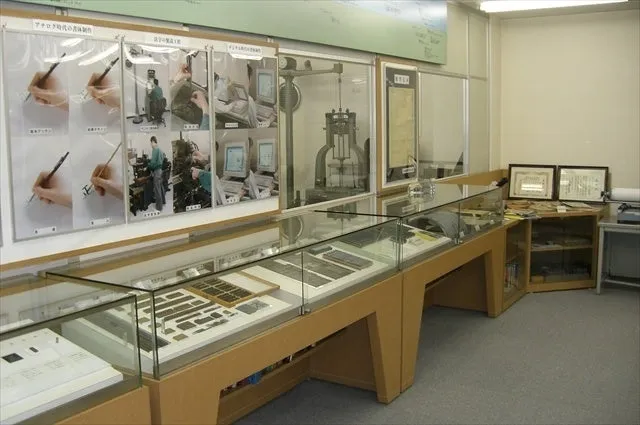
活字を鋳造し、活版印刷の版ができるまで
それでは、活字資料館の写真を何枚か掲載しながら、鋳造活字が製造される過程を簡単にご紹介します。
1)ベントン彫刻機
清書した文字の原図を基にしたパターン(亜鉛版)をなぞりながら、活字の母型(金型のようなもの)を作るのが、ベントン彫刻機です。この装置を操作してきれいな母型を作るのには熟練された技が必要だそうです。活版印刷で使われる鋳造活字は、日本語の文字の数だけ母型を作る必要があります。そして、サイズ単位(5号とか6号とか)毎に、活字を用意しなくてはなりません。それらの活字を鋳造するためには、母型が必要になるのです。
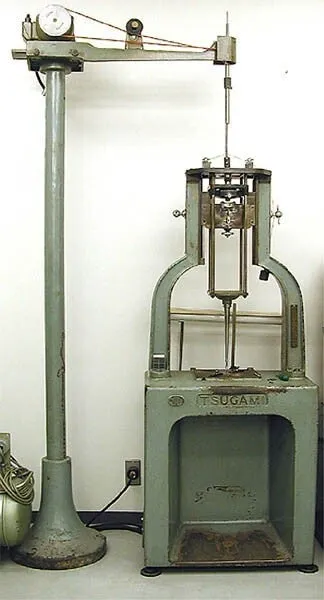
2)活字鋳造機
母型に地金を流し込んで活字を製造する機械です。地金の主な成分は鉛で、スズやアンチモンという素材も混ぜるようです。地金を熱して液状になったものを母型に流し込み、冷やすと、凸型の活字が完成します。
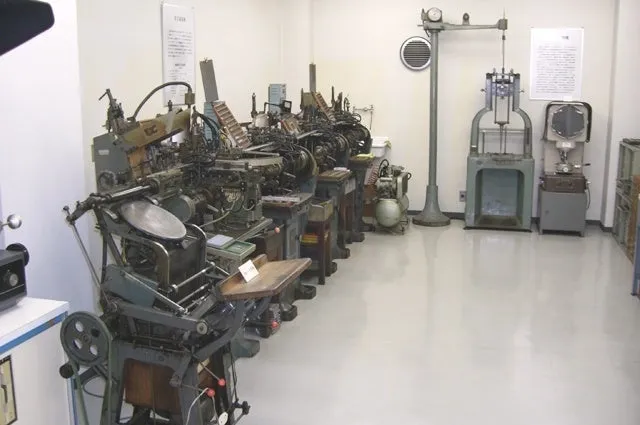
3)植字台で組版
鋳造活字が並べられた活字棚から活字を一つ一つ拾い(文選といいます)、そのあと、植字台で文字間や行送りを調整する小さいパーツ(インテルやクワタ)と組み合わせながら活字を組版していきます。最後に枠を糸でしっかりと縛ります。1万字以上ある膨大な日本語活字を文選して組版する作業ってすごいです。「文字を紡ぐ」という感覚ですね。
ところで、それぞれの文字、何本ずつ製造するのでしょうか? 例えば、ひらがな「の」は使用頻度が高いのでたくさん作る必要があったそうです。今なら、ビッグデータ分析で、文字の使用頻度の分布が数値化できますが、その頃は、経験値の積み上げから判断していたようです。また、小説と週刊誌とでは、よく使われる文字の傾向は違うでしょうし、業界毎に特殊文字や外字が存在するので、特注で文字を鋳造することもあったとお聞きしました。
書体毎に「原字」(文字デザイン)を作成し、そこからベントン彫刻機で母型を作り、鋳造機で金属活字をサイズ毎に製造するといった作業を、モトヤでは行っていたのです。デジタルフォントの世界から比べると気が遠くなる作業です。そんな文字の歴史を知ってしまうと、文字がますます愛おしくなります。
和文タイプライター、DTPシステムへ
欧文の活字タイプライターの文字の数は100字あれば、通常は間にあいます。ところが、日本語のタイプライターを作ろうとすると、必要な文字数って膨大です。日本語は英文の字数に比べて100倍以上ありそうです。モトヤ活字資料館には、日本語タイプライターのような機材が展示してありました。欧文タイプライターのようにタイピングしないので日本語タイプライターという表現は正しくないのかもしれません。資料館に展示してある活字組版装置には日本語の金属活字がずらっと収まっていました。それらの活字を拾い上げ、紙が巻いてあるプラテンに打鍵するとインクリボンから紙に文字が転写されて文章が完成するのです。文字を拾う方法は、手動で必要な文字を一つ一つ拾う方式と、文字盤から拾って電動式で活字を打鍵する方式がありました。
商品名にモトヤ「タイプレス」と書かれています。この「タイプレス」という組版機は、1970年代に広く普及していました。
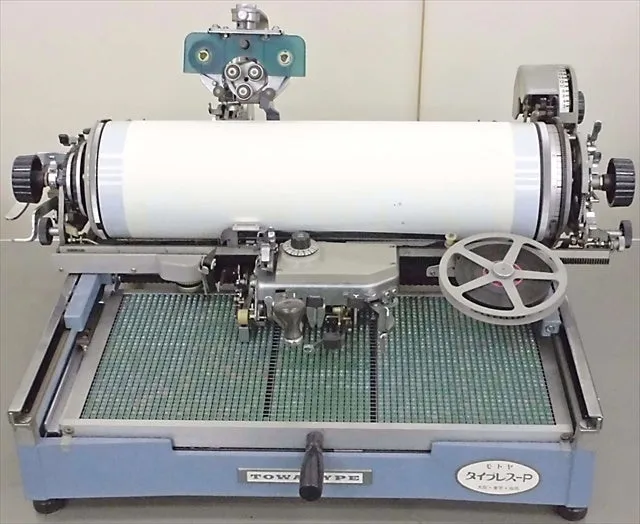
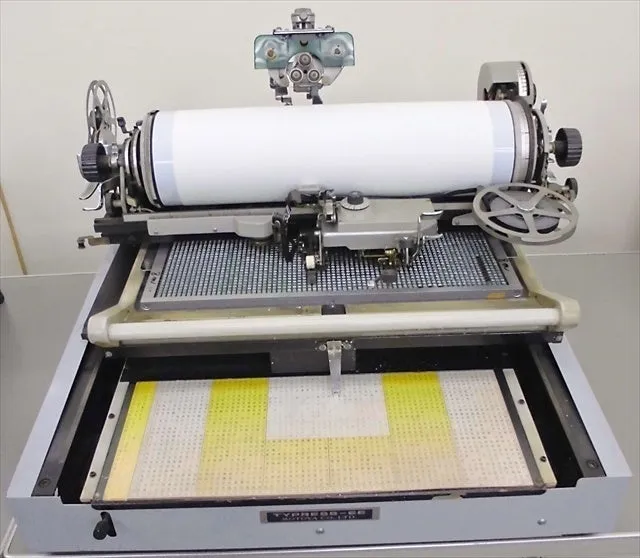
1980年代初頭に電子編集可能な組版機器が普及しはじめます。モトヤでは、1982年に「電子編集組版機WP-6000」を九州松下電気と共同開発しワープロの長所を取り入れた組版機を発売します。1985年にはレーザープリンタを搭載した「電子編集組版システムLASER7」シリーズが発売され、1988年にこの機材の分野にて販売量で業界シェア1位になりました。
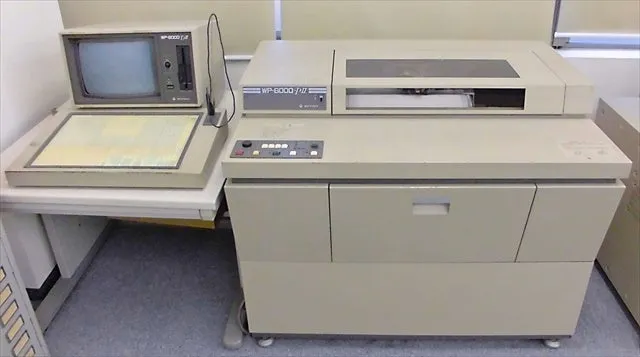
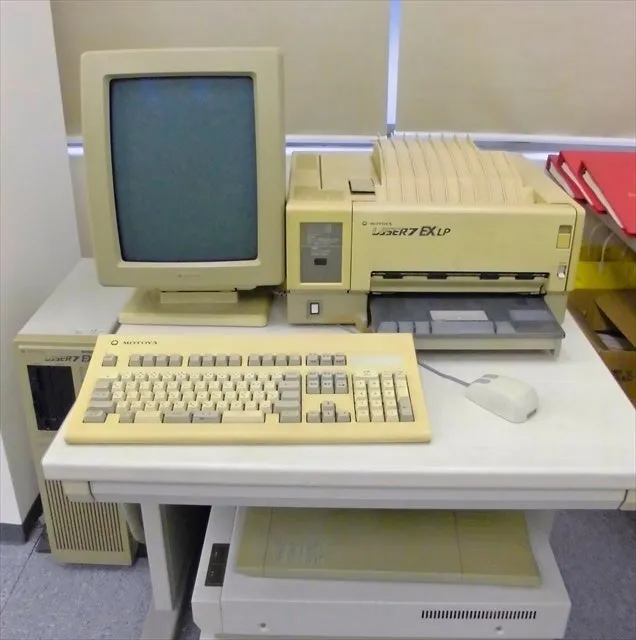
1980年後半、パーソナルワープロが家庭に普及し、ワープロの累計出荷台数は2,000万台を超えたと言われています。当時のワープロ専用機の多くに、モトヤの明朝体(ドットフォント)が採用されていました。また、モトヤ書体は写真植字(写植)のメーカーへも提供されました。
その後、インターネットの普及により、パソコンやスマホの画面越しにフォントを目にする機会が増え、時代が文字に求めるニーズはデジタルフォントへ変化しました。地図メーカーのウェブサイトではモトヤフォントが採用され、スマホメーカーのシステムフォントにも採用されました。パソコンやインターネットで求められるフォントサービスに柔軟に対応しています。
モトヤ書体の紹介
FONTPLUSで使えるモトヤ書体(69書体)の中から、主な書体をためし書きしてみました。
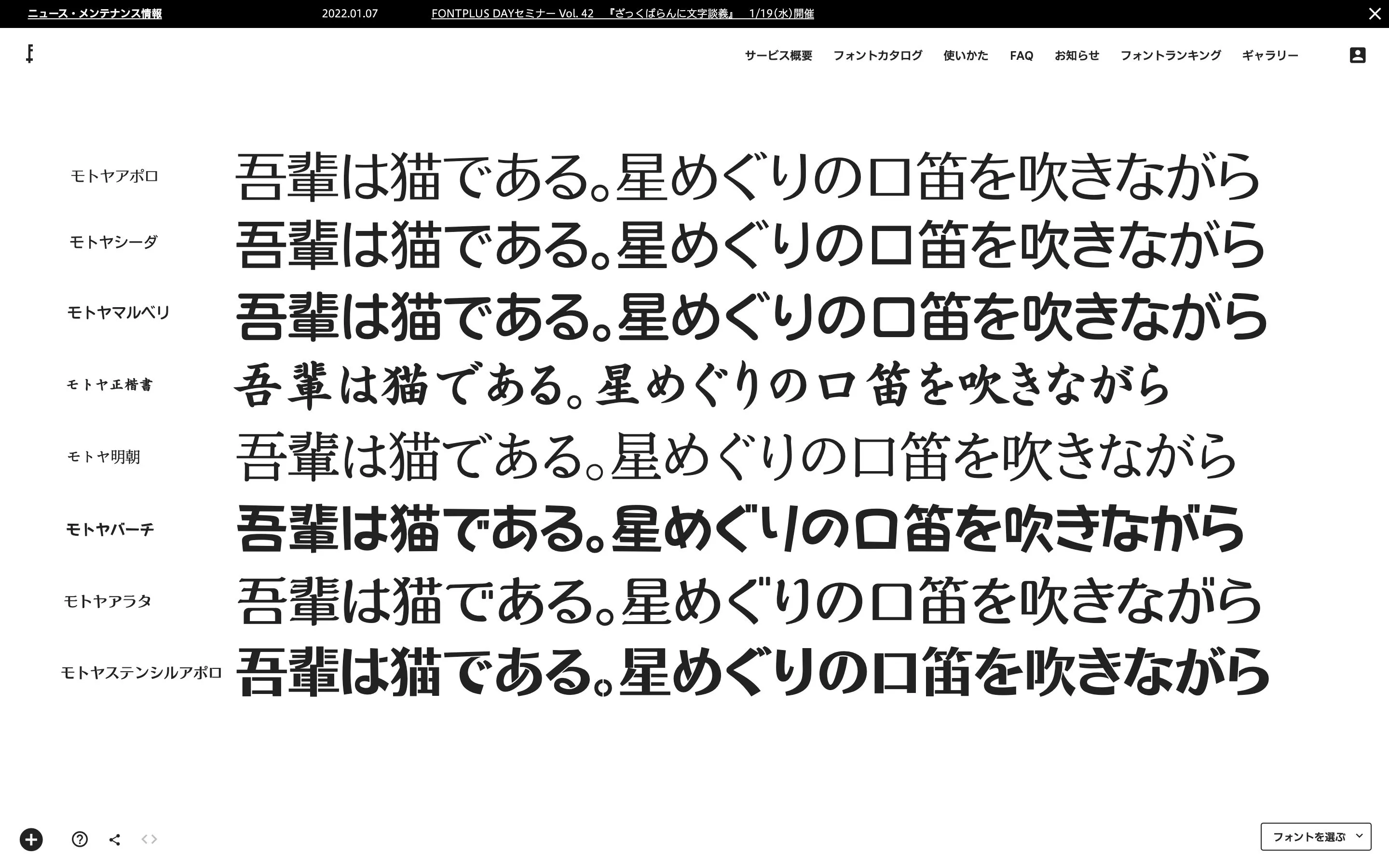
「モトヤアポロ」と「モトヤステンシルアポロ」は個性があり、素敵な書体です。「星めぐり」などのキャッチコピーに似合う書体で、FONTPLUSでも人気の書体です。そして、モトヤ書体として歴史があり、有名な書体といえば、「モトヤ正楷書」と「モトヤ明朝」です。では、モトヤ書体の中で人気書体のいくつかを詳しく解説します。
モトヤアポロ
「モトヤアポロ」は1969年米国宇宙船アポロが、月面着陸に成功した年に生まれた書体です。ドイツの有名自動車メーカーの宣伝広告を担うなど、モトヤ書体の花形として様々な分野で活躍しています。最近では、明るく清廉なイメージが好印象に繋がるとしてプレゼン用の書体として人気があり、力強さの中に読み易さを兼ね備えた、誰にでも素直に読み取っていただける書体です。
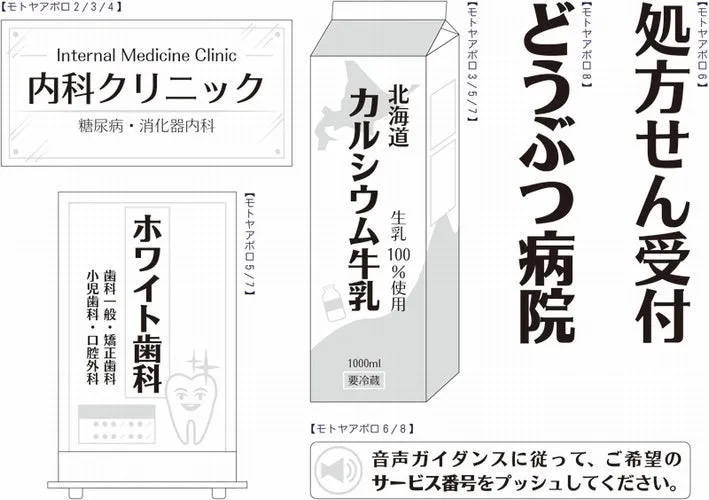
モトヤシーダ
伝統的な「モトヤゴシック」に対し、現代的なゴシック体として「モトヤシーダ」が1998年にリリースされました。「モトヤシーダ」は、文字の懐(ふところ)を最大限に広げ、従来のゴシック体の特徴であった縦棒、横線のラッパ状のアクセントである背勢表現を無くし、直線的ですっきりとしたデザインの書体です。
モトヤマルベリ
「モトヤマルベリ」は「モトヤシーダ」の特徴を受け継いだ丸ゴシック体です。「モトヤマルベリ」の開発にあたっては、懐を更に広げたり、仮名に丸みを持たせたりし、より丸ゴシックらしく見せるための処理を施しています。その結果、マルベリは充分な丸みを持ちながらも、シーダの特徴であるスッキリとした印象を併せ持った書体に仕上がっています。
モトヤ正楷書
戦後の日本の楷書体活字は、戦災により一部消失に加え、複製を繰り返したことなどを理由に、寄せ集めのようでした。そのような状況の中、書家であり書体デザイナーの山田博人氏が、唐を代表する欧陽詢の楷書を基に、統一された考えのもと、字並びや文字の大小、線の太さに不揃いがないように整理統合し、1957年に「モトヤ正楷書」を完成させました。通常、金属活字は鋳造時にカッターで活字の4面のバリ取りを行うため、ボディからはみ出ることはありません。しかし「モトヤ正楷書」の活字は「しんにょう」などが活字のボディからはみ出ており、毛筆の味わいと伸びやかな筆遣いが再現されています。
モトヤ明朝
モトヤ書体の礎を築いたのは、朝日新聞社で活字彫刻を手掛けていた太佐源三氏です。モトヤに招聘された太佐氏は、それまでの豊富な経験と技術を活かして1952年に初のモトヤ書体となる、「モトヤ明朝」を完成させました。「モトヤ明朝」は、造形の基本を「書」に置いた漢字と、様々な形からなる仮名のデザインをできるだけ正方へ近づけることで縦組にも横組にも適した、美しく可読性の高い書体です。